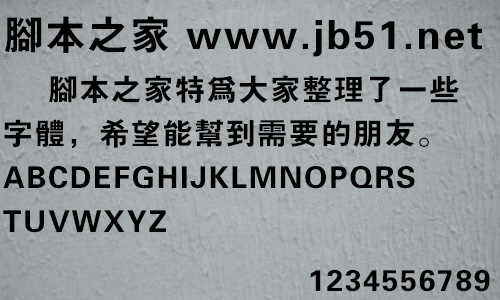
方正粗黑繁體字體是方正字體庫(kù)中的一種繁體字體,該字體筆觸較為粗實(shí),適合應(yīng)用于藝術(shù)設(shè)計(jì)、平面宣傳設(shè)計(jì)、網(wǎng)頁(yè)設(shè)計(jì),書(shū)法字帖等領(lǐng)域。喜歡的朋友們可以前來(lái)下載使用。